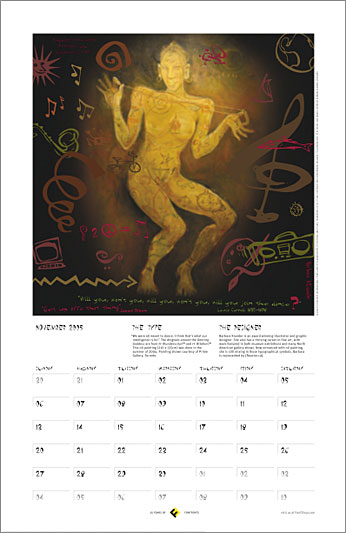
Kalenderblatt: Barbara Klunders goettlicher NovemberJüngst wiedergefunden: den FontFont-Wandkalender
2005. Weil es im Januar keinen tagesaktuellen Fontblog gab,
veröffentlichen wir die Monatsblätter erst jetzt. Die mehrfach
ausgezeichnete Illustratorin Barbare Klunder gestaltete das November-Motiv.
Basis ist ihr Ölgemälde »Tanzende Göttin«, das sie mit
Zitaten von Lewis Carroll und James Brown – gesetzt aus ihren Schriften FF
![]() Barbara Klunder: »Wir sind für das Tanzen bestimmt. Ich glaube,
hierfür wurden wir mit Intelligenz ausgestattet. Die Dingbats um
›Dancing Goddess‹ stammen aus den Schriften FF Klunder Script und FF
Ottofont. Das Ölbild (210 x 135 cm) entstand im Sommer 2004.
Veröffentlicht mit freundlicher Genehmigung der Prime Gallery,
Toronto.«